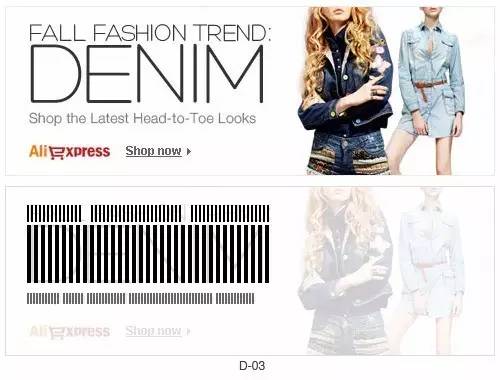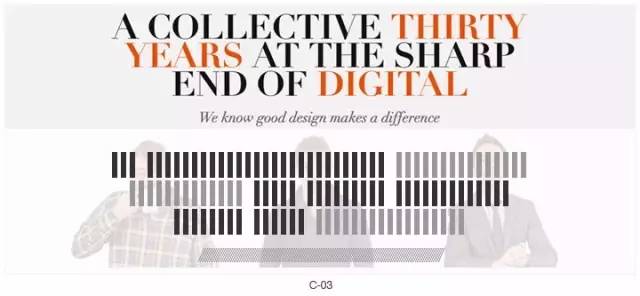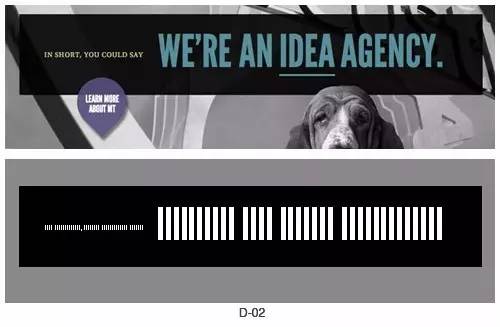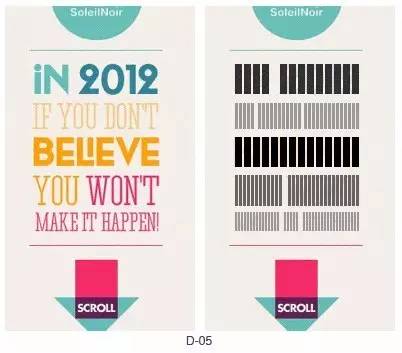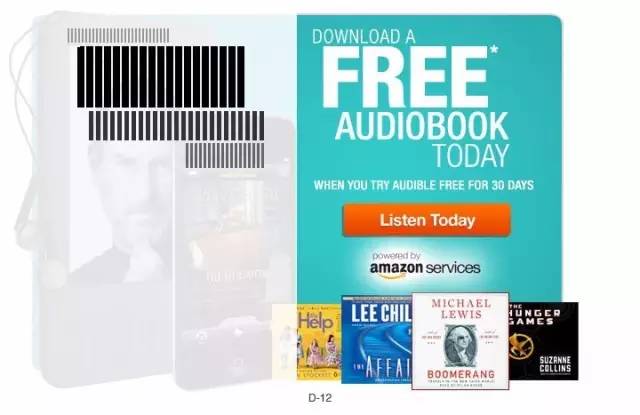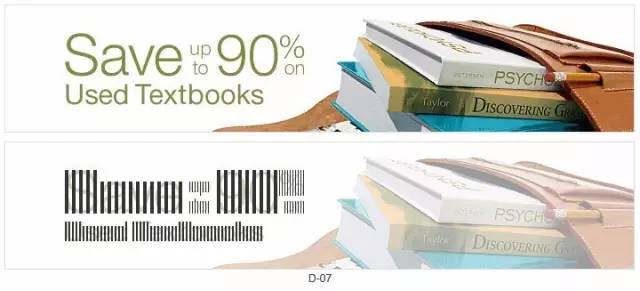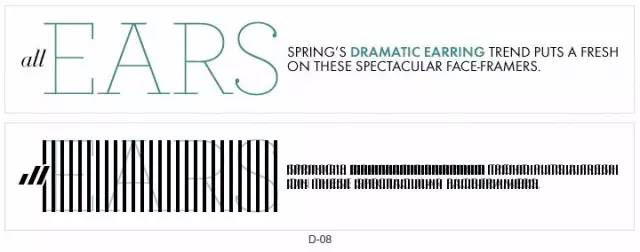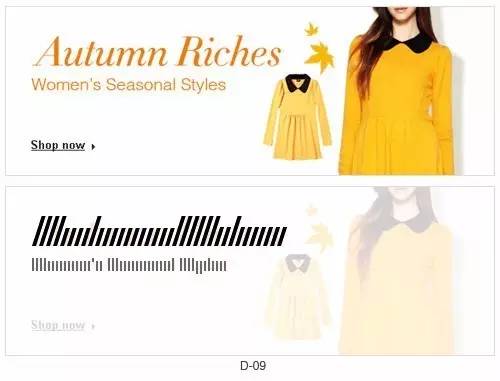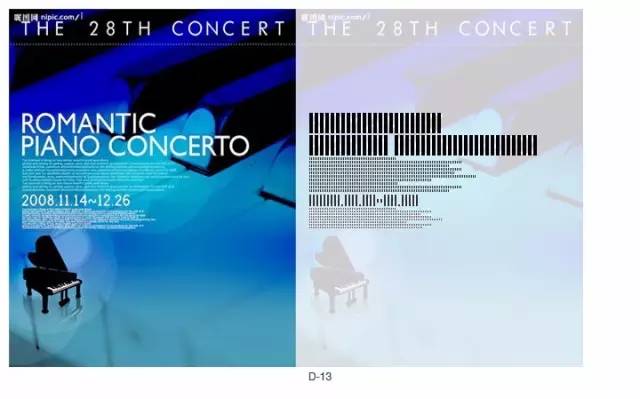
如何做好字体的排版设计,分享四大字体排版设计技巧。
作为设计师的我们,每天都在与字体打交道,我们常常希望能很好的使用他们,为设计加油添彩。我们常常纳闷,电脑里这么多的字体,要用哪一个?文字有这么多,怎样排版才能表达内心深处的思想?
常常说,艺术是相通的。将文字排版与音乐结合起来,用视觉化的音乐和文字排版相结合,会让我们的字体排版更容易组合,更能体现我们的设计情感。
将普通的文字赋予音乐的艺术形式,将文字排版赋予听觉的美感和视觉的美妙,更容易传递信息,表达其深层次的涵义。
当音乐响起时,电脑播放器里变化雀跃的频谱图,音响喇叭发生震动产生的声波,跳动的五线谱和乐器发生引起的变化图(A-01),都是我们体现情感的视觉化形式。
将文字排版用一个视觉化音乐的片段体现出来,从视觉上形成高度错落、疏密聚散、轻重缓急的效果,就具备了曲调的功能。
而一个优秀的字体排版设计,则成为一段具有节奏和韵律的音乐,我们可以理解为是一首凝固的音乐。
(一) 文字分析: 了解字体的结构和字体的特性,是我们排版优秀的字体的依据。
字体排版设计中,点线面结合成的设计群体,高低错落、疏密聚散,是构成形式美的重要因素。26个英文字母,根据字体的粗细设定节点组合,每个单独的字母就构成了音符。
如图(B-01),大写的I=1个长节点,O=4个长节点;如图(B-02),小写的a=3个短节点,b=1个长节点+2个短节点。
单行文字排版的横向韵律:根据字体的粗细设定节点的粗细和排布疏密,就能产生轻重缓急高低错落的节奏感和韵律感,如图(B-03)。
多行文字排版的纵向韵律:根据单行文字的长短和字体的粗细产生节奏和韵律,如图(B-04)。
当我们将文字音符化之后,就可以开始整理出字体排版的规律,使我们的字体设计更富韵律感。
(二)文字的韵律: 优秀的字体排版,具有其独特的美。由文字的律动演绎出米美妙的音乐。
文字本身的韵律:按照客观字体的变化、运用常态的字体字符进行连续地排列,形成一种律动形式。
一段文案,不采用任何修饰与变化,字体字号颜色都不变,所产生的节奏是就是单词与单词之间的间隔,字体是唯一能体现情感的依据。
如下图,字体字号方向均相同,节点音符不断的重复出现,节奏就是单词之间字母之间的间距,而大小写的区分,则产生了高低起伏的韵律,字体的粗细使文字发散出欢快还是稳重的气息,如图(C-01)全部大写是平缓稳重的韵律,如图(C-02)采用大小写,则产生了高低起伏的韵律,而因为节点比之左边文字节点要细,所以会显得活泼一些。
如图(C-03)所有字母都大写,单词间的间隔形成节奏,而单词间的颜色轻重形成韵律,文字排版在横向韵律的基础上又形成了纵向韵律。采用的字体稳重而不失活泼,加上下方的斜体字,使得整个文字排版透露出男性的稳重基调而又不失轻松愉快的韵律。
字体排版设计的韵律美表现在重复上:可以是间距不同、形状相同的重复;也可以是形状不同、间距相同的重复;还可能是别的方式的单元重复。这种重复的首要条件是单元的相似性,或间距的规律性;其次是节奏的合逻辑性。
(三)如何赋予文字韵律: 在文字本身涵盖的韵律节奏基础上,人为赋予其新的韵律和节奏
使用基本的字体和字号,在不进行其他特意变化的情况下,根据文字本身的特点进行调整,使文字排版在横向上和纵向上都产生客观自然的韵律变化,使字体排版的律动更加连贯顺畅,赋予设计师所想体现的情感,如同音乐的曲风。
如图(D-01)字体相同,不同字号,不同粗细,不同颜色,形成效果不同的韵律。节点的粗细间距都可以给人不同的韵律感,欢快的、稳重的、活泼可爱的还是紧张舒缓的,更由于韵律的不同而有更明显的对比。
案例分析:
图(D-02),文字采用大写,以单词的间距为节奏,字号大小进行对比形成韵律的强弱,文字排版理性而有秩序,由细微的韵律引导,突然变化成强烈的声调,主题震撼,醒目突出。
图(D-03),词间距为节奏,字号大小进行强烈对比突出DENIM,又因为采用的细线字体,使整个画面的韵律时尚又圆润,符合女装的主题。
图(D-04),词间距为节奏,字号大小进行强烈对比。首先以轻柔的高低起伏的音乐进入,继而以强烈的音乐震撼全场,后续仍以轻柔的音乐做为补充,交响曲的韵律突出重点,节奏震撼明朗。
图(D-05),横向上看,词间距为节奏,字体的粗细对比形成音律强弱,字体颜色深浅加强了音律效果,纵向来看字体大小颜色形成强-弱-强-中-弱的韵律。
(三)如何赋予文字韵律-基线、特效: 通过改变排版方式,添加一些特别效果如倾斜或者是手写,使文字更具趣味性。
常用的方式如增加斜体使文字具有动感和趣味,如字行间进行叠加使文字产生双基线进而形成二重奏或者多重奏的韵律,如图(D-06)。
案例分析:
图(D-07),左边的字体排版主要以基线的变化为主韵律,由单基线变双基线,单曲变重奏。大小写的高低起伏变化,让文字突出了重点表达了主要内容,节奏又变的明快。
图(D-08),如果这个文字排版是一首曲子的话,从左到右,先是轻快的斜体韵律开头,突然变化出明快的细线条大曲调,吸引人注意,最后出现一连串低调的曲子补充,让人看到这个文字就明白,是时尚的饰品。特别是开始的斜体,让画面在女性的稳重中透露出活泼。
图(D-09),以斜体为主旋律,由文字的大小写为起伏,韵律优美。
(三)如何赋予文字韵律-长短句、字距: 通过文字的大小对比和字距,添加纵向韵律。
如图(D-10),单词间字体大小悬殊,文字大小写以及单词的断点形成横向韵律,但从字行来看,字行的长短不同、高度不同、间距不同则形成了纵向韵律,因此这类型的字体排版则具有双重韵律。
案例分析:
图(D-11),从纵向上看,长短句的排版方式,让人感觉这就是歌曲的旋律,加上富有重短轻长的旋律和轻松趣味的手写字,让画面透出一股趣味。
图(D-12),我们平常排版,总是喜欢用对齐的方式,而这个文字的排版则另辟蹊径,左右都不对其或者居中。但是从左边的节点来看,旋律由轻柔递进到重调,然后渐隐再轻柔,呈现出一股递进的变化关系,让画面旋律轻松透气,韵味十足。
图(D-13),这种字体排版的组合方式,既有横向韵律又有纵向韵律。横向上看,句子的字号对比,重-轻-微重-再轻以及单词间的节奏,纵向上看,句子长短的起伏和画面所体现的情感相呼应。
不做干扰韵律的设计:一套字体排版设计,字体采用两种最佳,最多不超过3种,在这个基础上对字体进行调整和变化,如大小写,字号、粗细、行间距以及一些特殊变化如斜体和双基线,就可以产生一系列的排版变化,使文字排版具有序列、对比、参差、强弱等等具备设计情感的节奏和韵律。
(四)韵律设计范例 : 字体排版的创作过程,自始至终伴随的是一种理性的情感体验。
字体排版的分析已经告一段落,如何将这种排版方式运用到我们的字体排版当中,下面用一个例子来说明。
图(E-01),一行没有变化的字,虽然有秩序,但是太长没有重点没有主次,只能依靠字体本身所具备的特性产生节奏,韵律平淡不出彩。
图(E-02),将平淡的句子断开,在原有的韵律基础上,赋予新的节奏。
图(E-03),但新的节奏不能够突出我们想突出的重点,我们要进行调整。这是一个注入我们情感关注的过程。
图(E-04),付诸我们主观意识希望赋予的情感,强调突出。改变字体大小、粗细对比等,调整节奏,形成新的韵律。将重点词汇调整突出,赋予情感,使节奏更加突出,旋律更加流畅。
图(E-05),细节调整,使韵律更加流畅。添加颜色能让韵律分出轻重刚柔,再加上斜体特效使得整个严肃的文字添加了一丝动感。
图(E-06),如此这般,因为节奏的不同,赋予的情感不同,可以产生不同的韵律。 根据以上的排版方法,我们就可以排列出具有不同特点的文字。
文字本身是千锤百炼的结晶,本身具有很美的韵律。经过设计和选用作为排版的基础,将字母用节点的方式代替,通过节点的长短粗细间距,让文字通过粗细高矮的变化以及字距行距的变化产生出重复、大小、颜色、基线形状、长短句的音乐,赋予文字节奏和韵律,就能产生出丰富多彩的视觉效果。